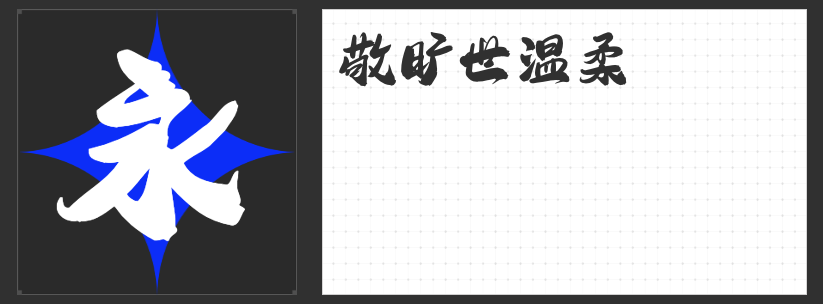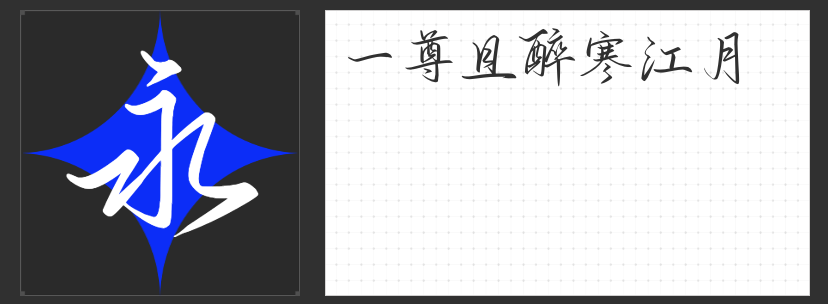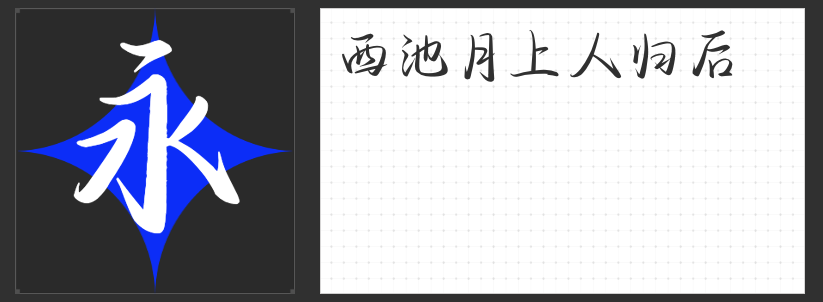
四款国潮设计专属字体:以笔墨丹青重塑东方美学新境
在国潮设计浪潮中,字体不仅是信息载体,更是文化基因的视觉转译。本文精选四款风格迥异却皆具东方气韵的字体,它们以传统书法为骨,现代审美为魂,为当代设计注入刚柔并济的美学力量。
一、造字侠侠道简繁
这款字体以饱满字形承载天地气度,回锋收笔处暗藏太极推手般的圆融之力。转折处适度夸张的飞白处理,既保留了毛笔触纸的原始质感,又通过布白均衡的章法布局,营造出"行到水穷处,坐看云起时"的禅意境界。其桀骜不驯的笔锋与松弛自然的结构形成微妙张力,恰似水墨画中留白与实景的对话。
二、字圈也字醉寒江行草
取法二王行草精髓,这款字体在起承转合间重构书写逻辑。优化后的笔迹既保留了"飘若浮云,矫若惊龙"的潇洒气韵,又通过精准的笔画控制确保识别度。每个字符都如同才子衣袂,在收放自如的节奏中展现东方美学的克制与浪漫,特别适合需要传递文化自信的设计场景。
三、字圈也字风满袖行楷
以楷书为基底,行书为血脉,这款字体在严谨结构中注入流动的诗意。左勾竖的锐利出锋与游丝引带的婉转形成视觉对冲,既保持了文字的骨骼清正,又通过牵丝勾连的笔意赋予其"银钩虿尾"的书法魅力。其荡气回肠的笔势,恰似传统武术中的刚柔相济之道。
四、造字侠侠义简繁
这款字体以圆转笔意破方折之规,通过勾挑牵丝的呼吸感构建文字生态。潇洒狂放的笔触中暗含八卦阵法的布局智慧,放纵流动的形态里沉淀着端方持重的文化基因。其大气磅礴的气势与收放自如的节奏,完美诠释了东方美学中"大巧若拙"的哲学境界。
这四款字体皆以传统书法为源,通过现代设计语言的重构,在保留文化基因的同时赋予其时代生命力。它们用笔墨的浓淡干湿、结构的疏密虚实,共同构建出属于这个时代的东方美学体系,为设计师提供了跨越时空的文化对话工具。